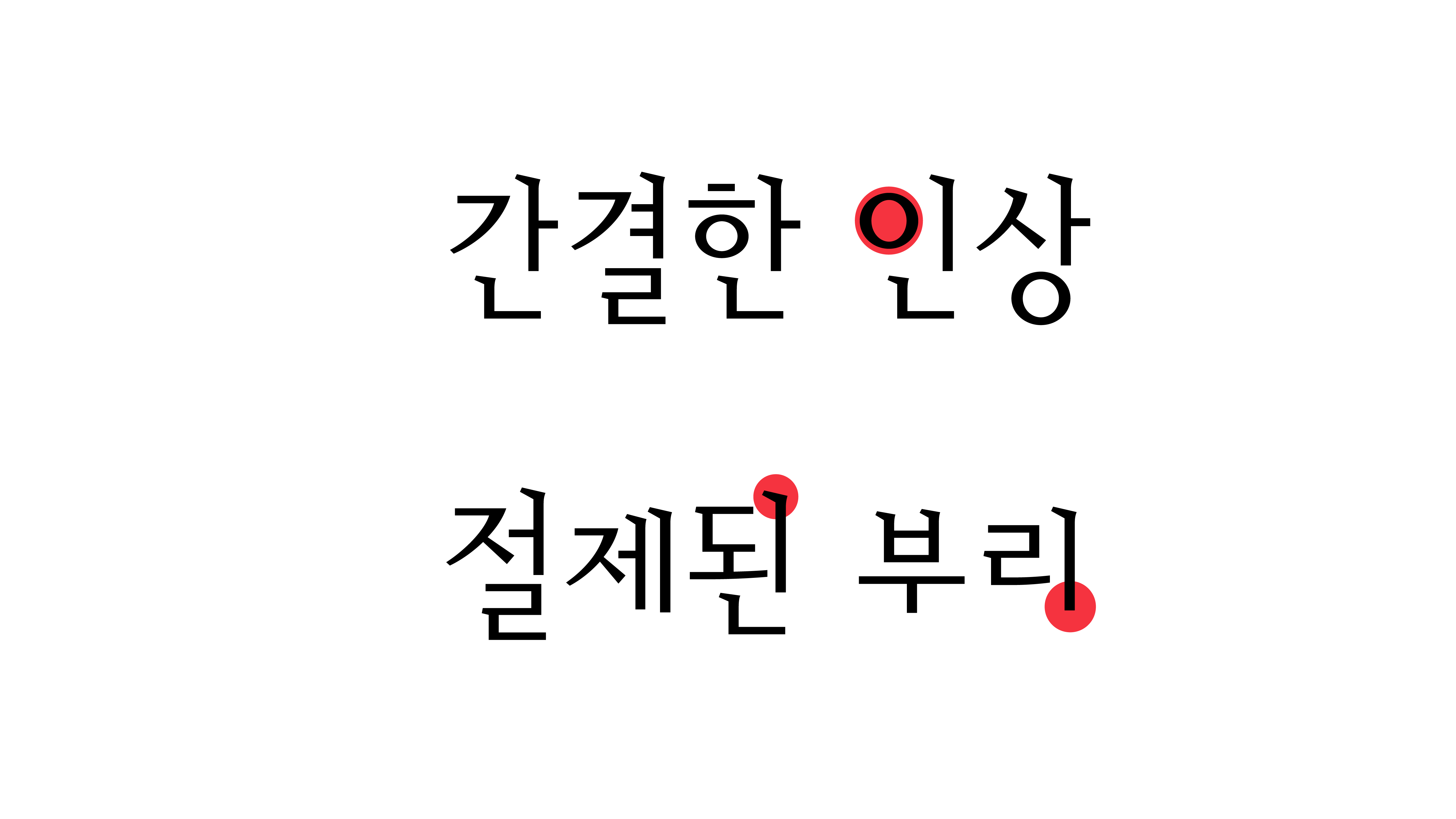
쉬리
Yoon 쉬리
단순하고 명료하다는 것은 어쩌면 폰트 디자인의 궁극적인 지향점인지도 모릅니다. 그리고 쉬리체는 그 기본적인 역할에 충실하게 디자인된 제목용 글꼴이지요. 간결한 인상과 뛰어난 판독성, 절제된 부리 표현을 통해 멋스러움까지 두루 갖춘 모범적 폰트. 쉬리체와 함께 완벽한 제목 표현에 도전하세요.